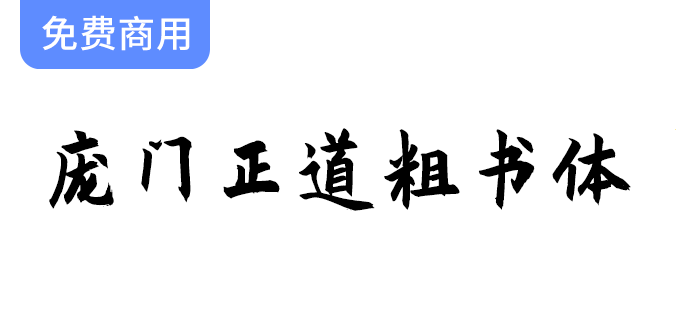
庞门正道粗书体正式版是一相当优秀的艺术类中文字体,庞门正道粗书体最新版便捷好用,字体字形笔触比较粗实,书写端正大气,庞门正道粗书体字体将书法感和设计融为一体,墨渍感十足,创意特点鲜明,应用性明显,能够应用于文本装潢、信息展示、网页设计、篆刻制模、数据制作、装潢设计、计算艺术设计、视觉设计、字帖等一切合法应用场景。